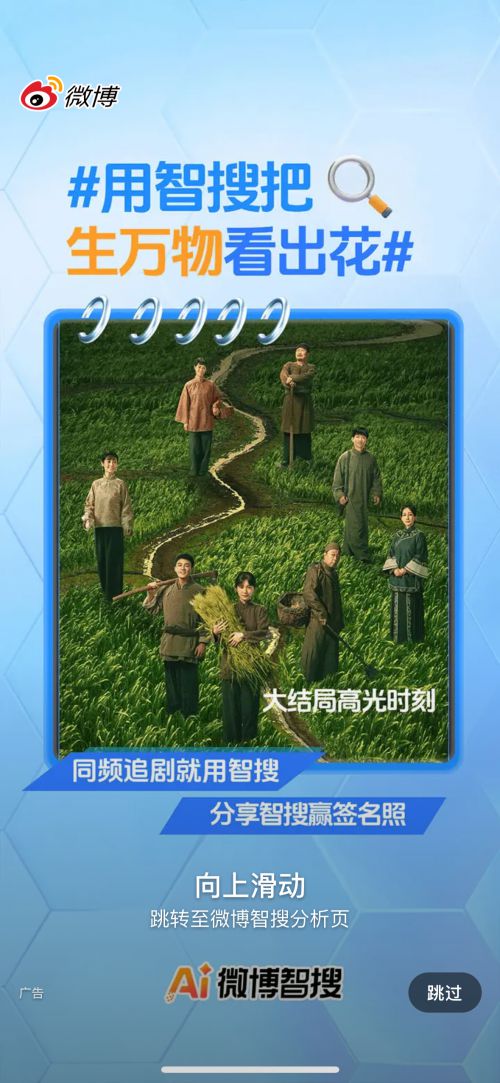
抖音美好体
抖音美好体是一款充满趣味的创意字体,以活泼设计传递轻松美好的视觉体验。字形偏方正,重心居中,中宫适中,整体布局稳重又不失灵动;笔型以直角为基调,搭配部分简洁装饰元素,方头笔画利落干脆,笔画连接多为断开处理,细节处尽显设计巧思。字身饱满粗壮,笔画粗细均匀,视觉张力十足,既保证了文字的清晰识别,又通过趣味笔触增添了活泼气息。 作为免费商用字体,抖音美好体支持简体中文常规字符集,适用于社交媒体配图、海报设计、品牌宣传等多元场景。无论是表达生活中的小确幸,还是展现创意灵感,都能以独特的字形语言点亮画面,让文字传递的不仅是信息,更是愉悦的情绪。用抖音美好体,让每一次设计都充满惊喜,让每一段文字都自带美好滤镜。